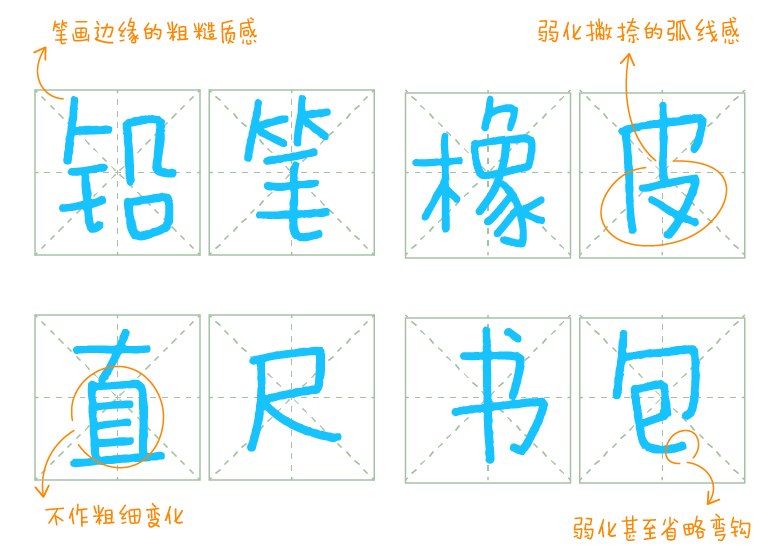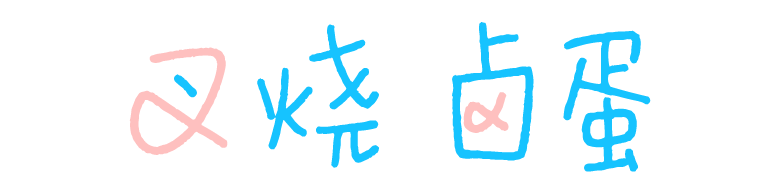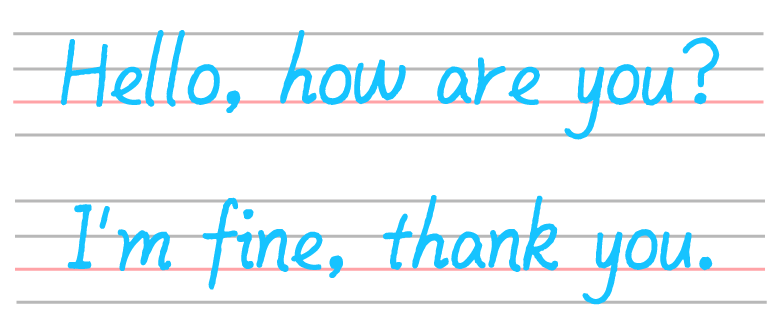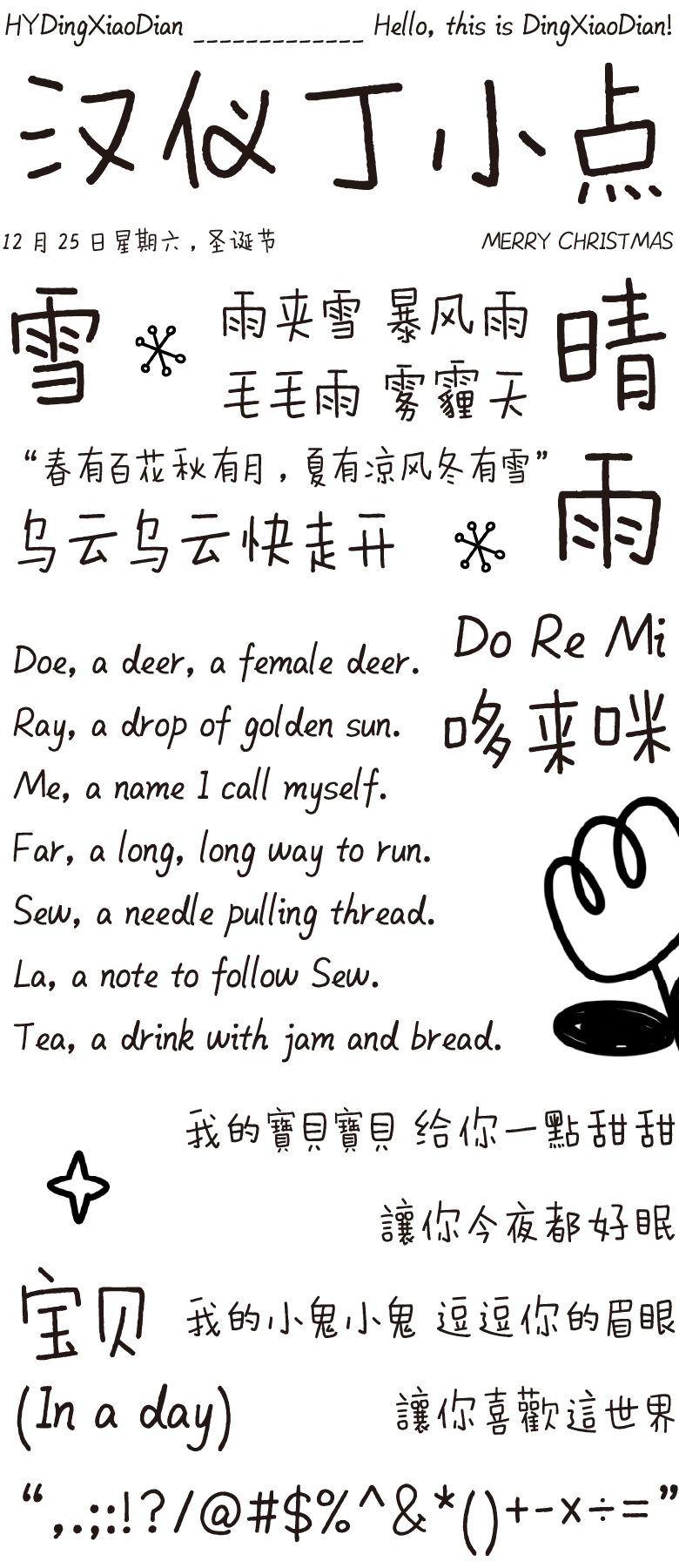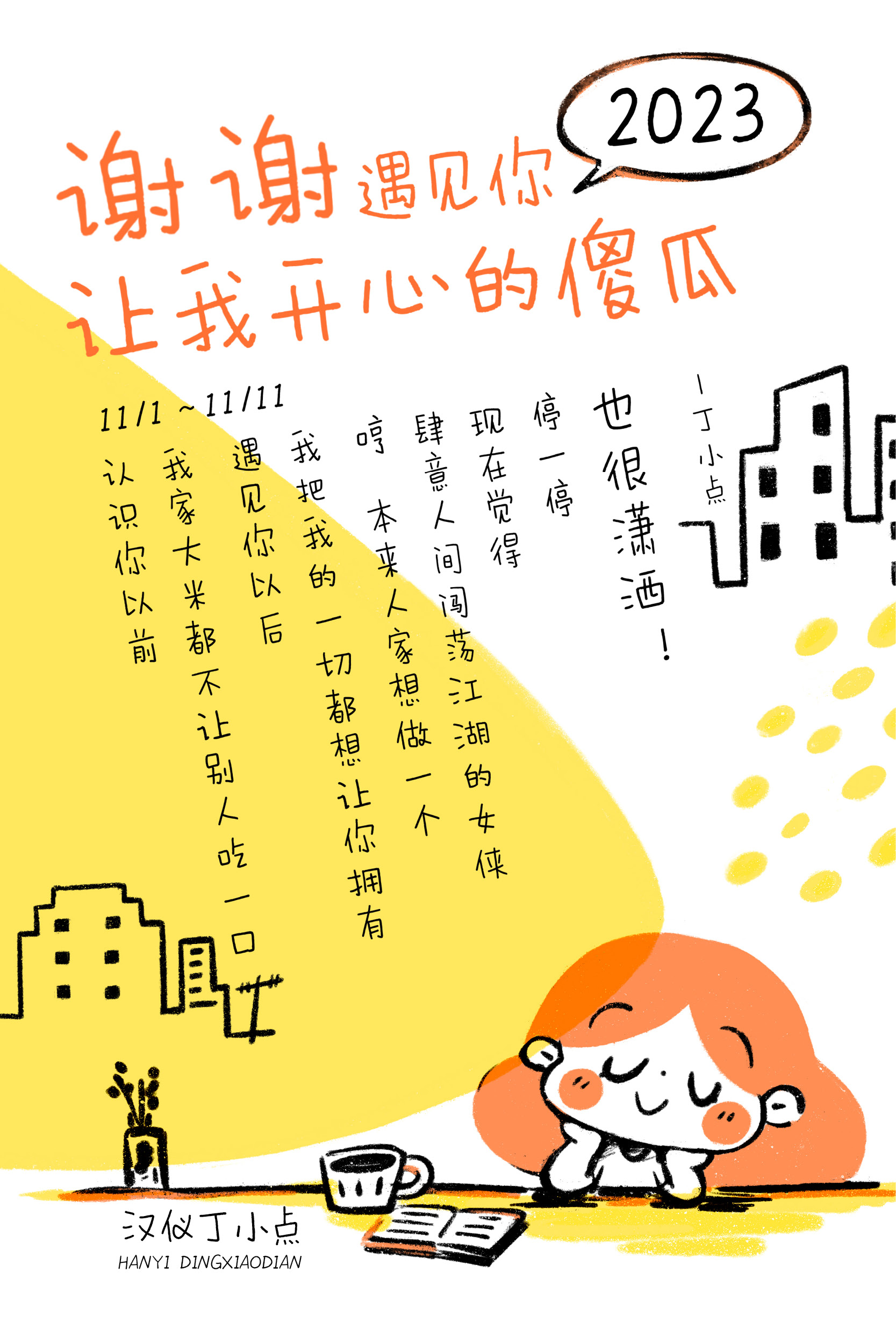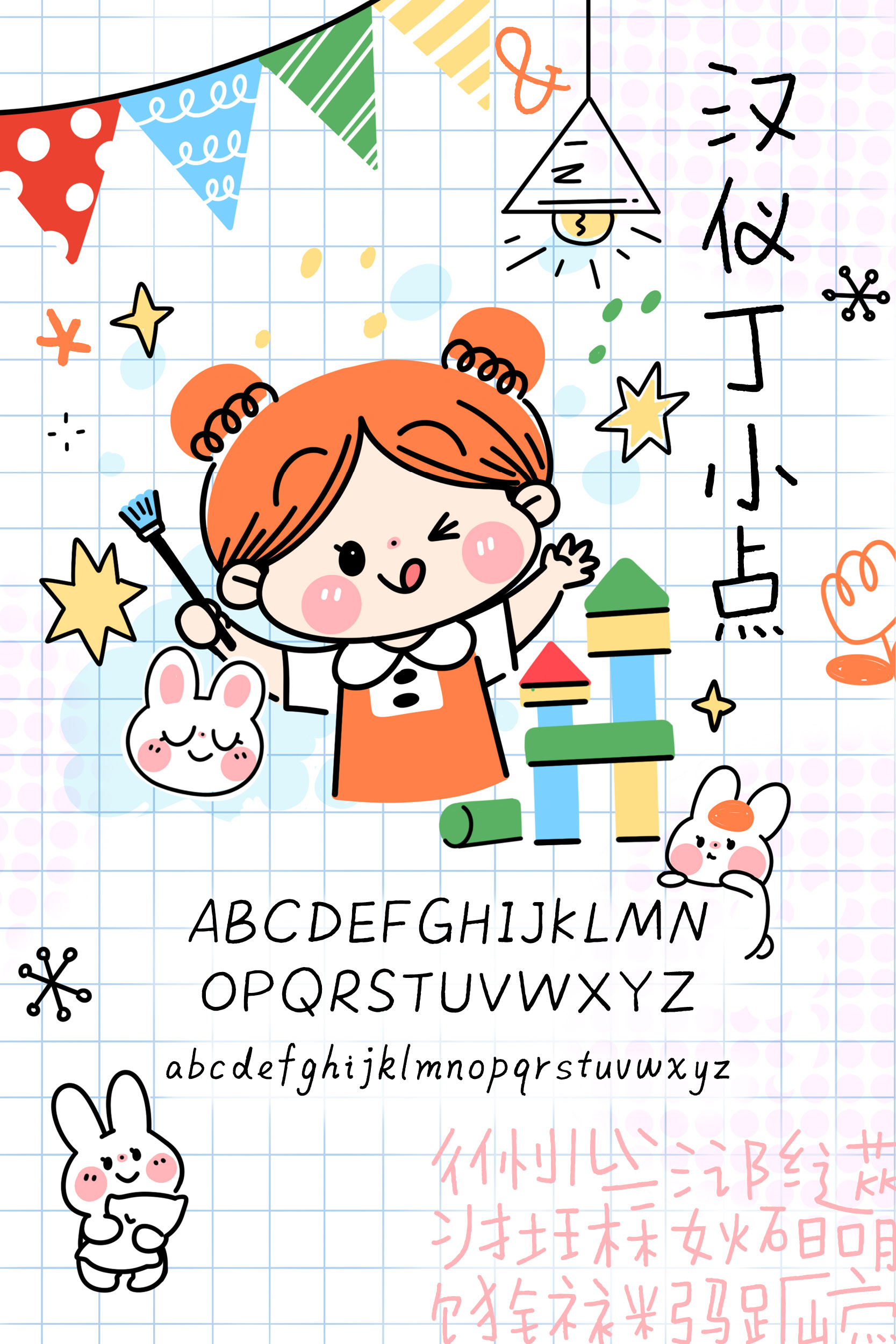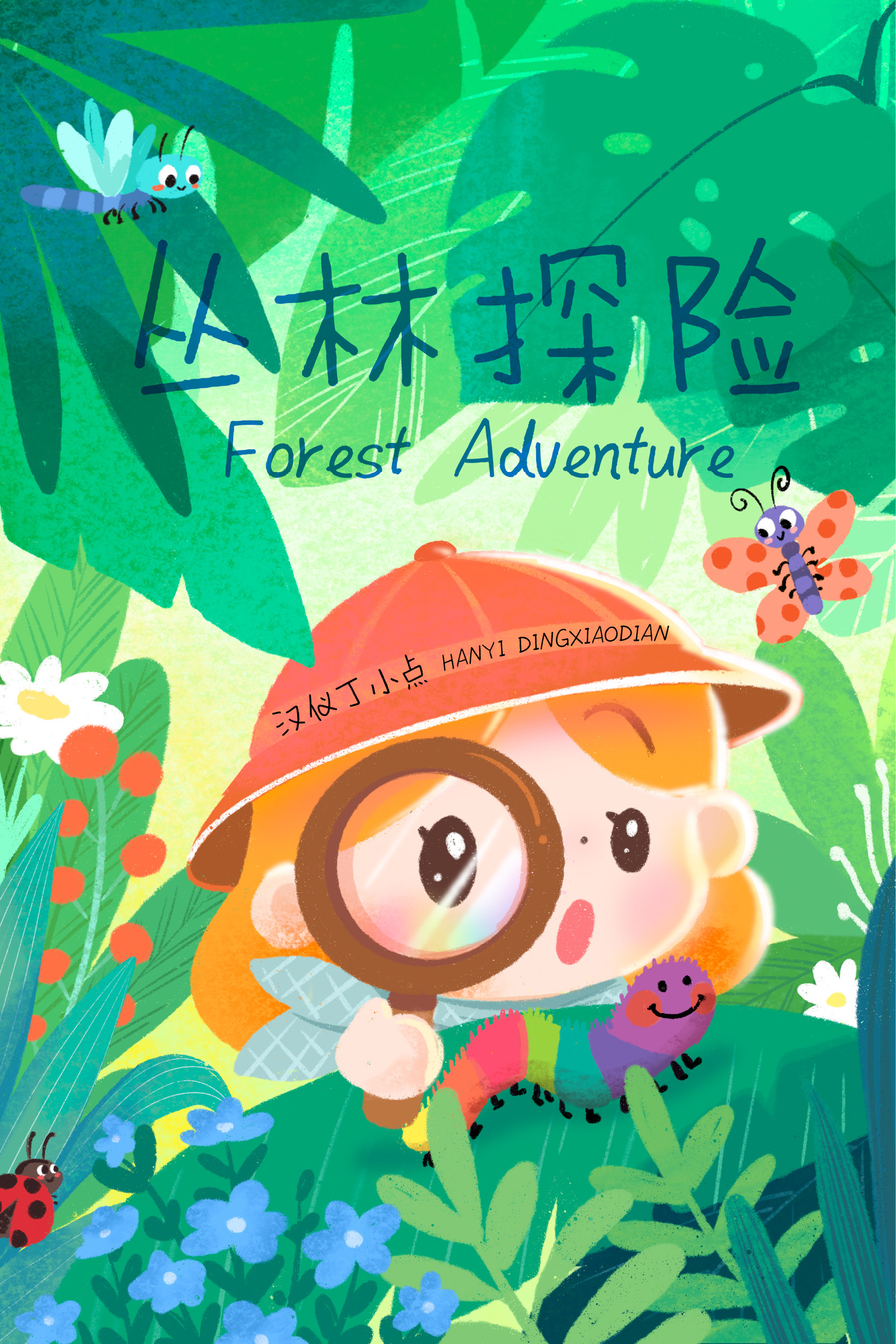
重回记忆中的铅笔字体
书写字体 – 漫画风
漫画 / 可爱 / 童稚 / 趣味 / 活泼
标志 / 书籍 / 广告 / 杂志 / 游戏 / 动漫 / 影视 / 包装
汉仪丁小点是由汉仪字库签约作者、漫画家丁小点创作的首款字体作品。这款字体就像是记忆中青涩的铅笔字,书写出丁小点成长中的点点滴滴。这款充满稚趣的漫画字体可以作为标题和内文字体完美应用于漫画绘本、儿童读物、玩具周边等多种场景。
这款字体字形放松,整体微微收窄而避免了字形过于松散。整体结构上松下紧,呈现出不同于常规字体的童稚趣味。
字面大小依字形而有变化,各部件的穿插组合灵活,字形整齐统一又不失活泼。
这款字体的笔画不作粗细变化,并弱化了弧线弯钩等显露书写气质的笔画,就像可爱的儿童的铅笔字。
笔画衔接处的留白像是在认真的一笔一画之间喘了口气,简洁之中凸显手写的稚拙。
撇捺之间的简单连笔俏皮而略带青涩,写出对成长的渴望。
汉仪丁小点的西文设计同样还原了学生时代认真写字的感觉,中西文匹配可以满足更丰富的内容使用需求。